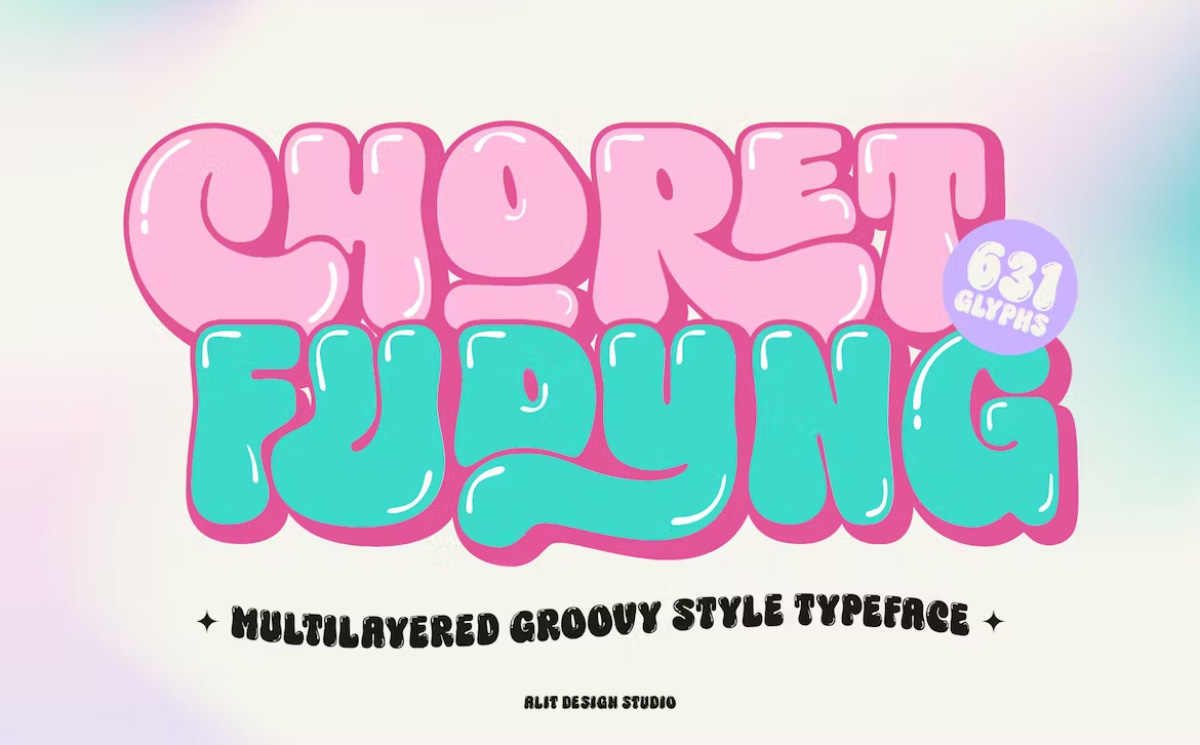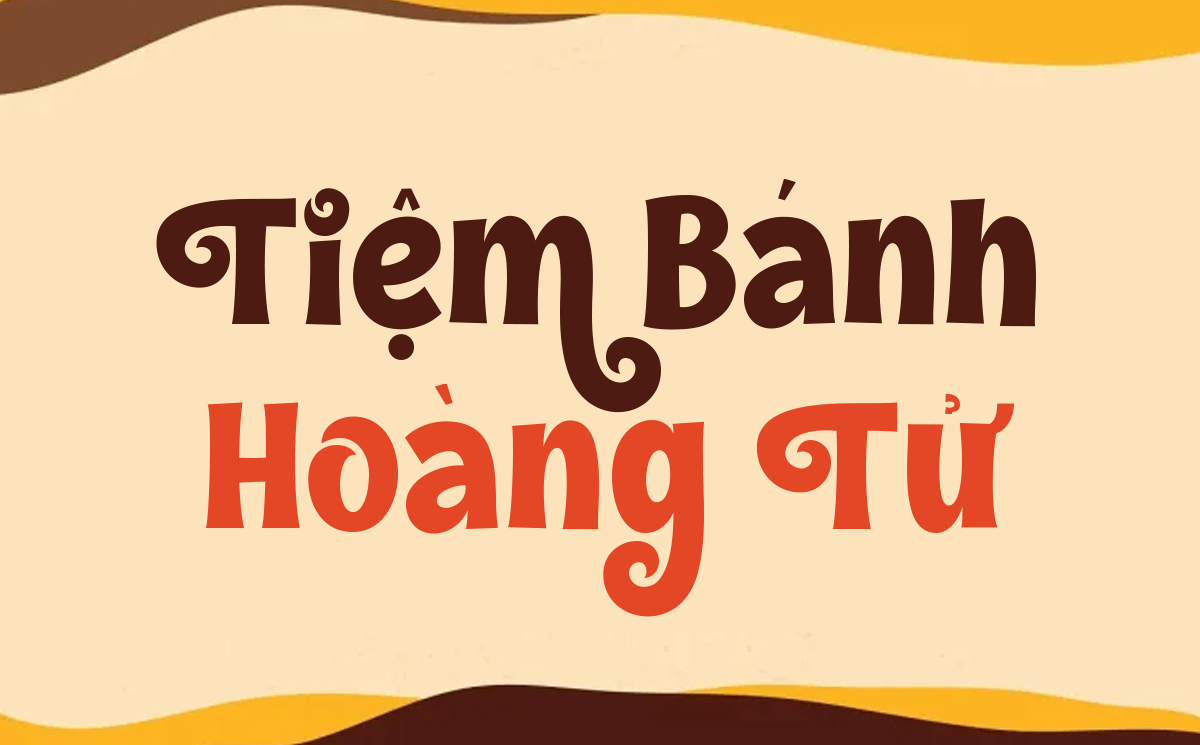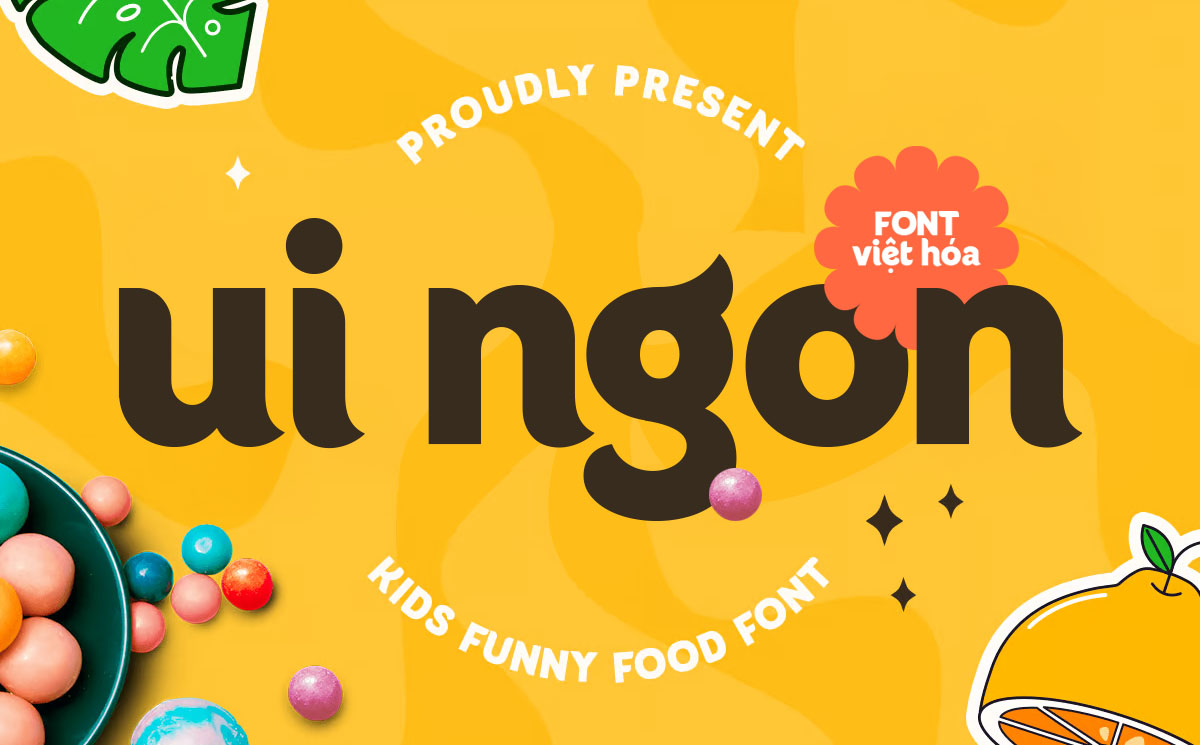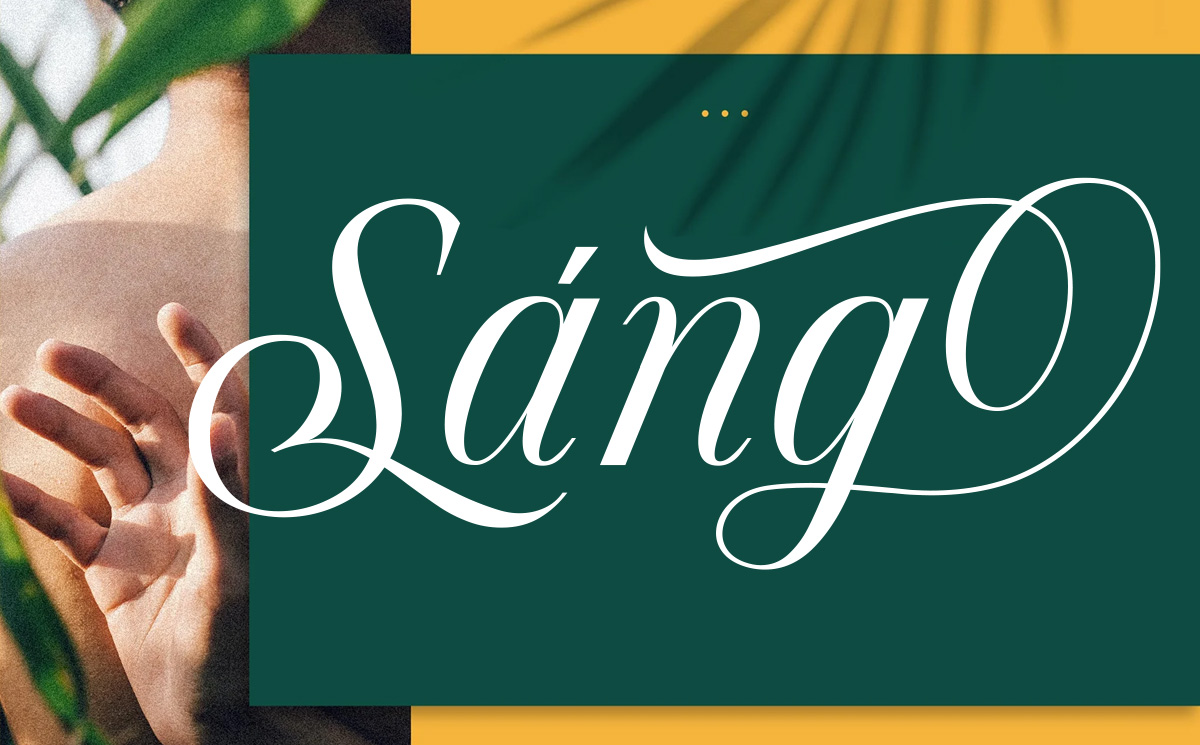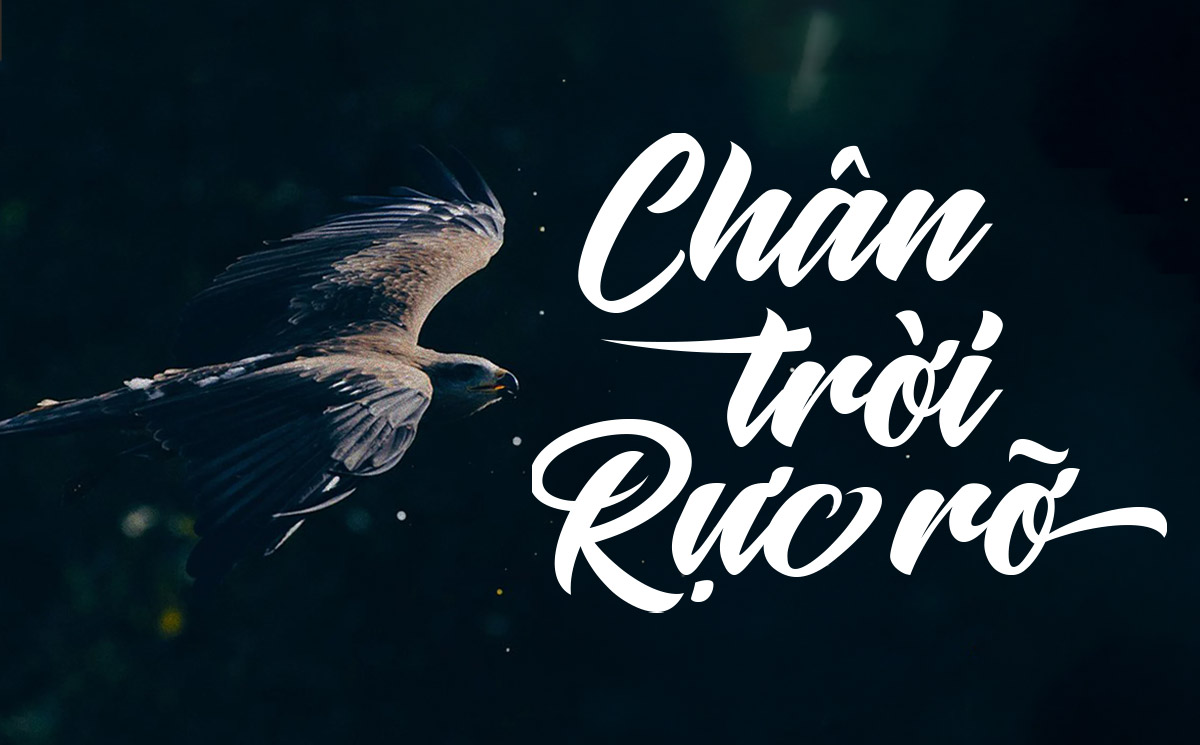
Top 15 font chữ cho sticker, tem nhãn handmade và shop phụ kiện dễ thương
Gợi ý 15 font TH Việt hóa phù hợp để thiết kế sticker, tem nhãn handmade, bao bì mini và hình ảnh cho shop phụ kiện dễ thương.
Sticker, tem nhãn handmade và hình ảnh cho shop phụ kiện thường có diện tích rất nhỏ. Chỉ một cụm chữ như “handmade”, “thank you”, “made with love”, “trà dâu”, “móc khóa cute” hay tên shop cũng cần đủ dễ đọc, đủ có cá tính và đủ hợp với sản phẩm. Vì vậy, chọn font sticker Việt hóa không nên chỉ nhìn vào độ dễ thương. Font còn phải giữ được dấu tiếng Việt, không bị rối khi in nhỏ và phù hợp với phong cách thương hiệu.
Với các shop bán phụ kiện, đồ len, móc khóa, sticker pack, bánh kẹo handmade, nến thơm, mỹ phẩm mini hoặc quà tặng nhỏ, font chữ là một phần của cảm giác “đáng yêu” mà khách nhận được khi mở gói hàng. Một tem nhãn đẹp có thể làm sản phẩm trông chỉn chu hơn, còn một font khó đọc sẽ khiến thiết kế mất điểm dù màu sắc và hình minh họa rất xinh.
Danh sách dưới đây gợi ý 15 font TH Việt hóa phù hợp cho sticker, tem nhãn handmade và shop phụ kiện dễ thương. Các font được chọn theo hướng không lặp lại những font đã giới thiệu ở các bài trước, đồng thời chia thành nhiều sắc thái: hoạt hình béo tròn, chữ viết tay, nét mềm, vui tươi và đáng yêu.
Cách chọn font sticker Việt hóa cho tem nhãn nhỏ
Các tiêu chí để chọn font sticker Việt hóa cho tem nhãn nhỏ bạn nên biết
Ưu tiên khả năng đọc ở kích thước nhỏ
Sticker và tem nhãn thường được in ở kích thước vài centimet. Font quá nhiều nét xoắn, nét mảnh hoặc chi tiết trang trí sẽ dễ mất khi in. Trước khi chốt font, hãy thu nhỏ thiết kế về đúng kích thước thật và đọc thử trong 2-3 giây.
Kiểm tra dấu tiếng Việt trước khi xuất file
Tên sản phẩm handmade hay shop phụ kiện thường dùng tiếng Việt có dấu: “bé xinh”, “trà đào”, “nến thơm”, “vòng tay”, “kẹo dẻo”, “móc khóa”. Font thiếu dấu hoặc dấu quá sát chữ sẽ làm nhãn trông thiếu chuyên nghiệp. Hãy gõ thử nội dung thật trước khi dựng hàng loạt mẫu.
Chỉ dùng font cute cho phần cần nổi bật
Font cute hợp tên sản phẩm, headline, câu cảm ơn hoặc sticker nhấn. Với thành phần, hướng dẫn bảo quản, số điện thoại, mã đơn hoặc thông tin nhỏ, nên dùng kiểu chữ đơn giản hơn. Nếu toàn bộ tem đều dùng một font trang trí, thiết kế sẽ nhanh bị rối.
Chọn font theo tính cách sản phẩm
Sticker cho bánh kẹo cần cảm giác ngọt và vui. Tem nến thơm handmade cần mềm và ấm. Shop phụ kiện trẻ trung cần chữ có năng lượng. Quà tặng cao cấp hơn có thể dùng nét viết tay mảnh. Khi font khớp sản phẩm, thiết kế nhìn tự nhiên hơn nhiều.
Top 15 font TH cho sticker, tem nhãn handmade và shop phụ kiện
1. TH Cartoon 1 - chữ béo tròn cho sticker vui nhộn
TH Cartoon 1 phù hợp với sticker pack, nhãn đồ ăn vặt, tem bánh kẹo, sản phẩm dành cho trẻ em hoặc các shop muốn tạo cảm giác vui ngay từ cái nhìn đầu tiên. Dáng chữ béo tròn giúp headline nổi bật trên nền màu pastel, nền kẻ caro hoặc nền minh họa nhỏ.
Khi dùng TH Cartoon 1, hãy đặt font cho tên sản phẩm hoặc câu ngắn như “ngọt xỉu”, “bé xinh”, “món quà nhỏ”. Với tem nhãn in nhỏ, nên tránh thêm stroke quá dày vì chữ vốn đã có khối lớn.
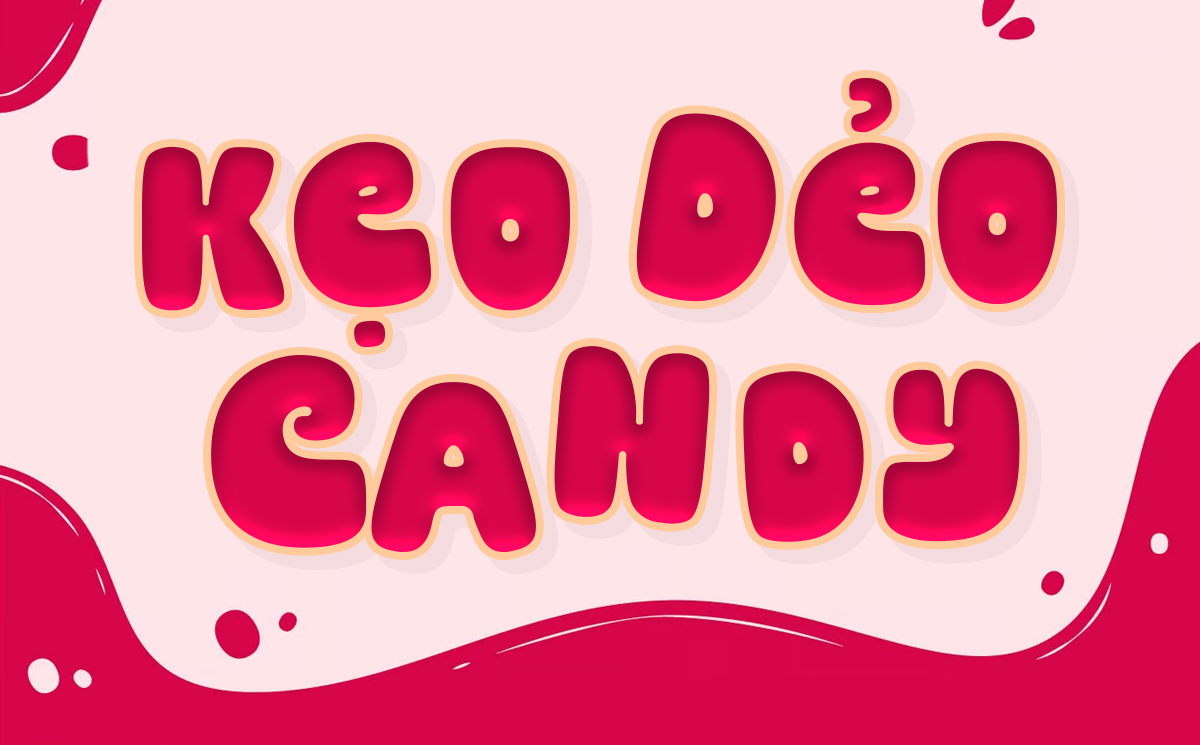
2. TH Cartoon 4 - phong cách cute cho shop phụ kiện
TH Cartoon 4 là lựa chọn hợp với shop móc khóa, phụ kiện tóc, sticker trang trí, ốp điện thoại hoặc quà tặng học sinh. Font mang cảm giác hoạt hình, dễ thương và thân thiện, phù hợp với các thiết kế cần sự tươi tắn.
Bạn có thể dùng font này cho logo phụ, nhãn dán cảm ơn, tiêu đề bộ sưu tập hoặc sticker sale nhỏ. Nếu shop có nhiều sản phẩm màu sắc, hãy giữ chữ một màu rõ ràng để không bị chìm trên nền.
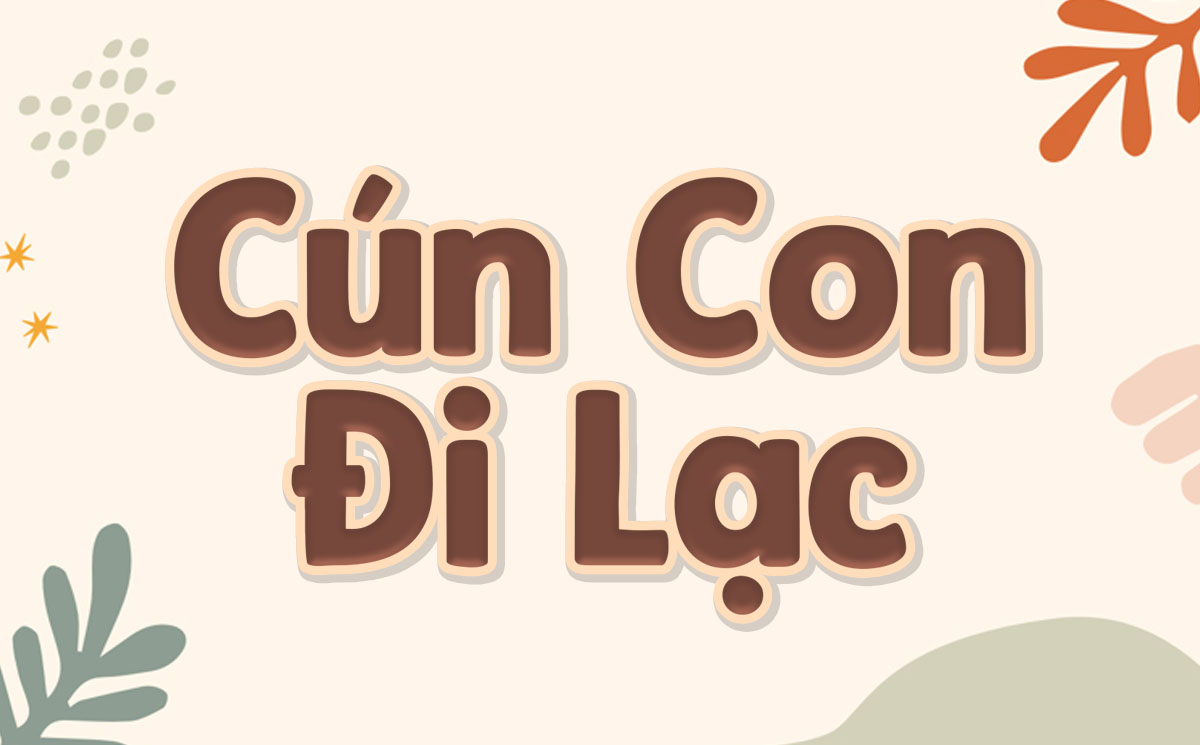
3. TH Cartoon 5 - font cho tem đồ ăn và nhãn bánh kẹo
TH Cartoon 5 hợp với lĩnh vực ẩm thực, đặc biệt là bánh handmade, snack, trà sữa, kẹo, nước trái cây hoặc các món ăn đóng gói nhỏ. Font có nét vui và gần gũi, giúp tem nhãn bớt khô mà vẫn giữ được khả năng nhận diện.
Với tem đồ ăn, hãy dùng TH Cartoon 5 cho tên vị hoặc tên món. Các thông tin như ngày sản xuất, hạn dùng, khối lượng nên đặt nhỏ hơn và dùng kiểu chữ gọn để người mua dễ đọc.
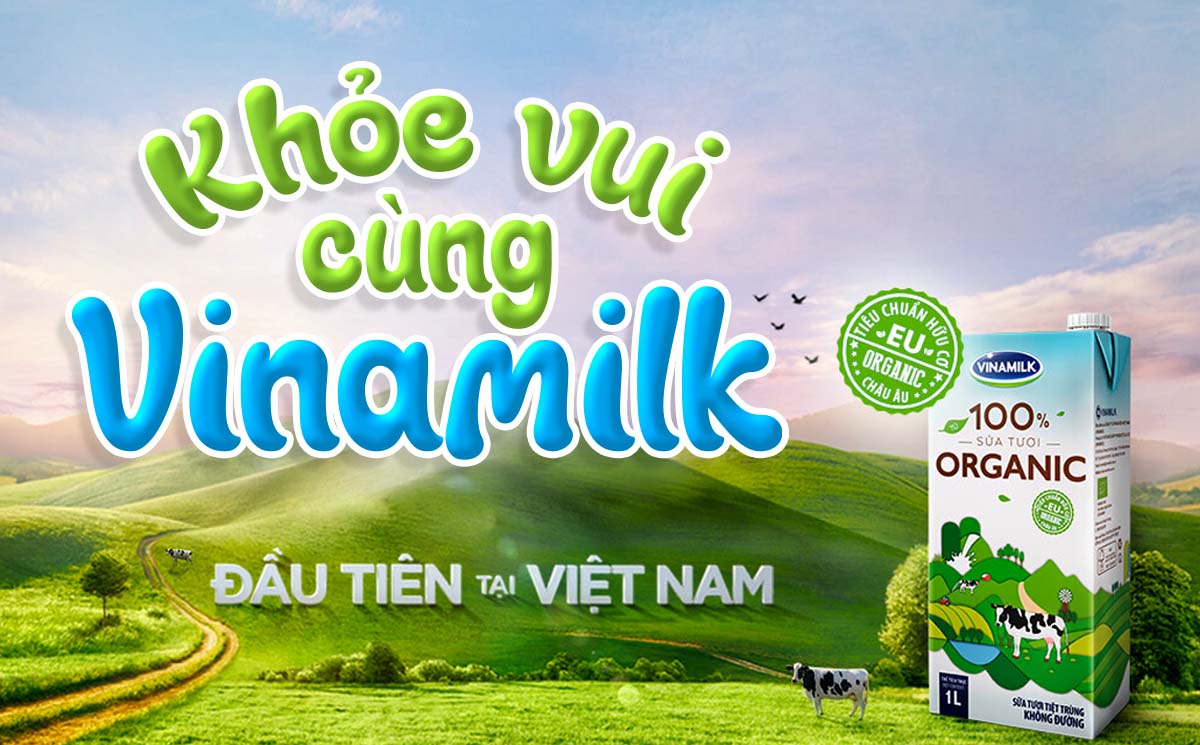
4. TH Cartoon 7 - mũm mĩm và đáng yêu cho sticker mini
TH Cartoon 7 có dáng mũm mĩm, hợp với sticker mini, nhãn đồ lưu niệm, hộp quà nhỏ và thiết kế có mascot. Font tạo cảm giác mềm, tròn và đáng yêu, rất hợp với nhóm sản phẩm “cute” đúng nghĩa.
Khi dùng cho sticker, nên đặt chữ ngắn, có khoảng trắng rộng và tránh để quá nhiều icon chen vào chữ. Chỉ cần một cụm chữ nổi bật là đủ làm sticker có cảm xúc.
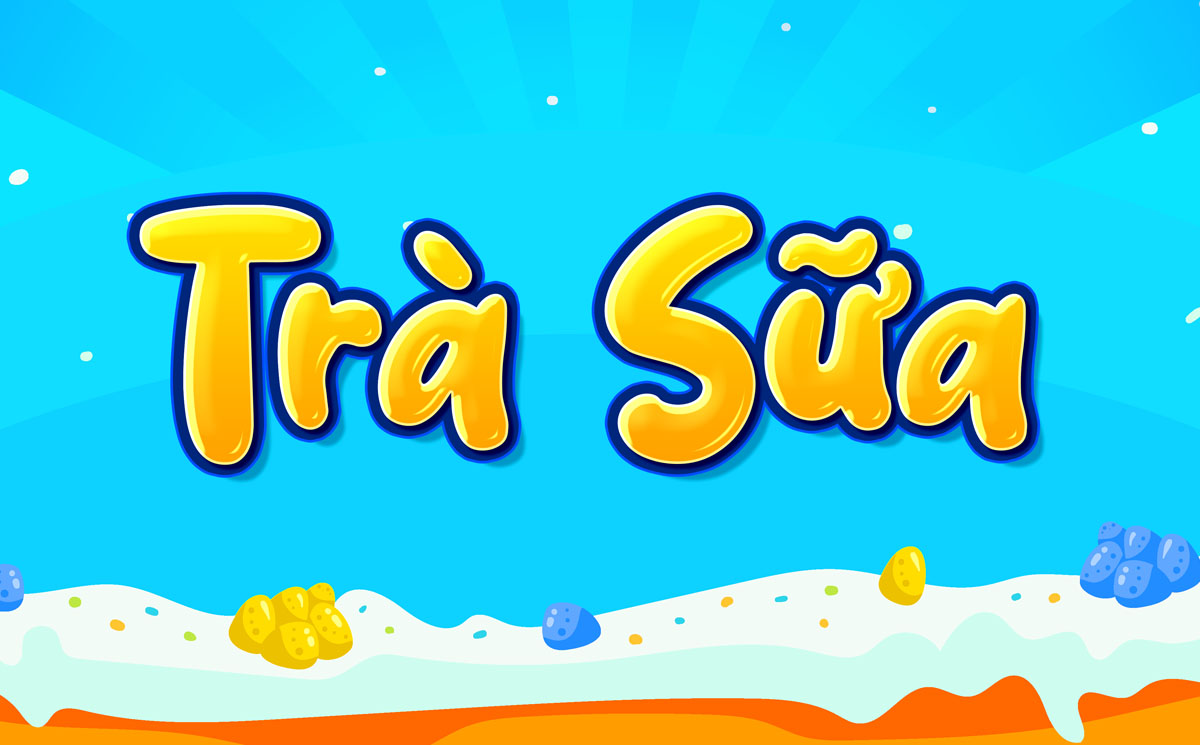
5. TH Choco Fantine - viết tay vui tươi cho đồ ăn handmade
TH Choco Fantine kết hợp cảm giác viết tay và hoạt hình, phù hợp với nhãn bánh quy, chocolate, kẹo dẻo, trà trái cây, sữa chua hoặc các sản phẩm ngọt. Font giúp thiết kế có cảm giác thủ công hơn so với các font hoạt hình quá tròn.
Khi thiết kế cho shop phụ kiện hoặc sản phẩm handmade, đừng chọn font chỉ vì nhìn xinh ở kích thước lớn. Hãy thử trên đúng nội dung thật, đúng kích thước in thật và đúng chất liệu tem nhãn. Một font TH Việt hóa phù hợp sẽ giúp sản phẩm nhỏ trông chỉn chu, có nhận diện và dễ khiến khách nhớ đến shop hơn.